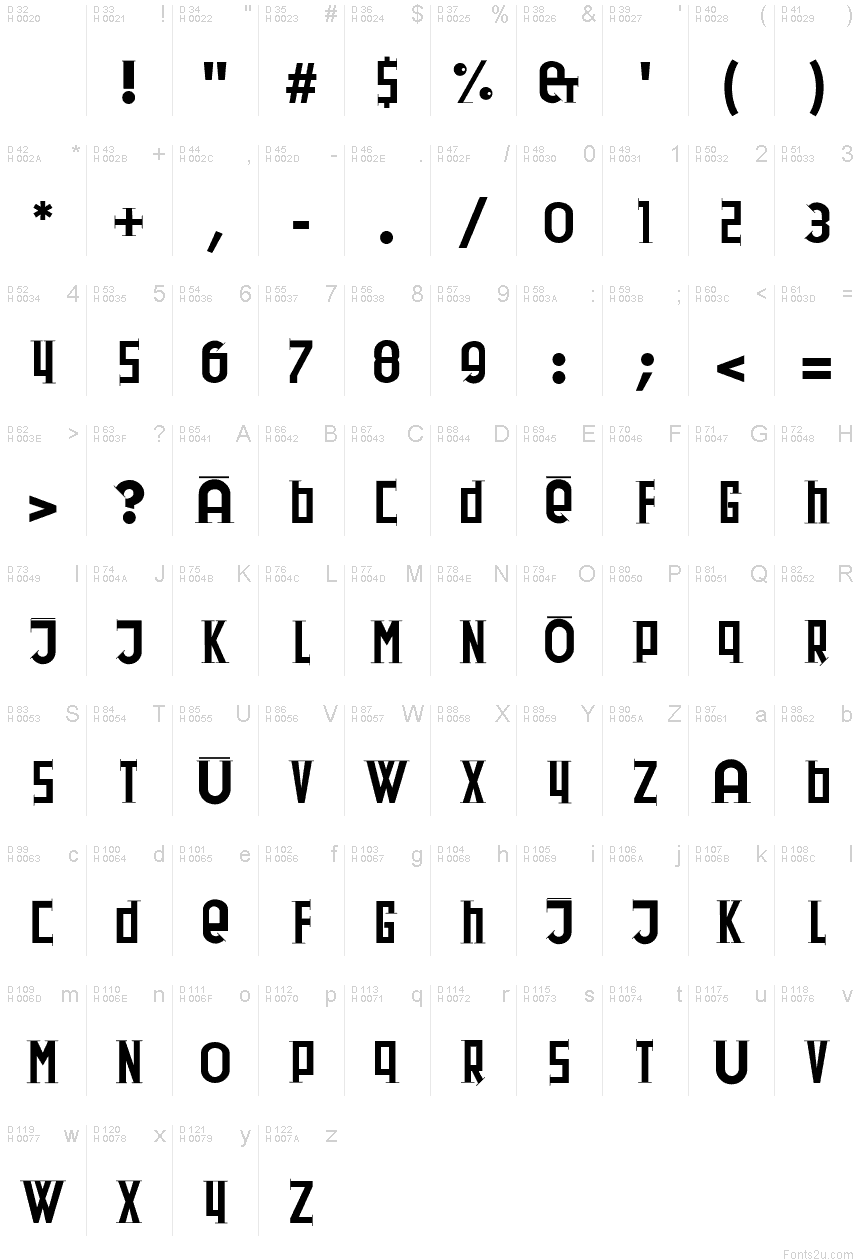
DadaDa Serif autorstwa M. Kleina to darmowy geometryczny krój szeryfowy typu display, zbudowany z wysokich, wąskich wielkich liter i surowych modularnych kształtów. Szerokie, zakrzywione szczyty spotykają się ze sztywnymi pionowymi kreskami, a delikatne, blokowe szeryfy i nisko osadzone poprzeczki nadają literom architektoniczny, artdecowski charakter.
Powtarzające się łuki nawiązują do drzwi, fasad i geometrycznych obramowań. Dzięki temu krój ten sprawdza się w projektach plakatów, oprawie graficznej wystaw, okładkach książek oraz identyfikacji wizualnej wydarzeń kulturalnych, gdzie litery mogą stać się częścią ilustrowanej struktury zamiast neutralnego podpisu. Jego najsilniejszym kontekstem jest design inspirowany dawnymi epokami, czerpiący z geometrycznych form ery maszyn i wczesnomodernistycznych ornamentów.